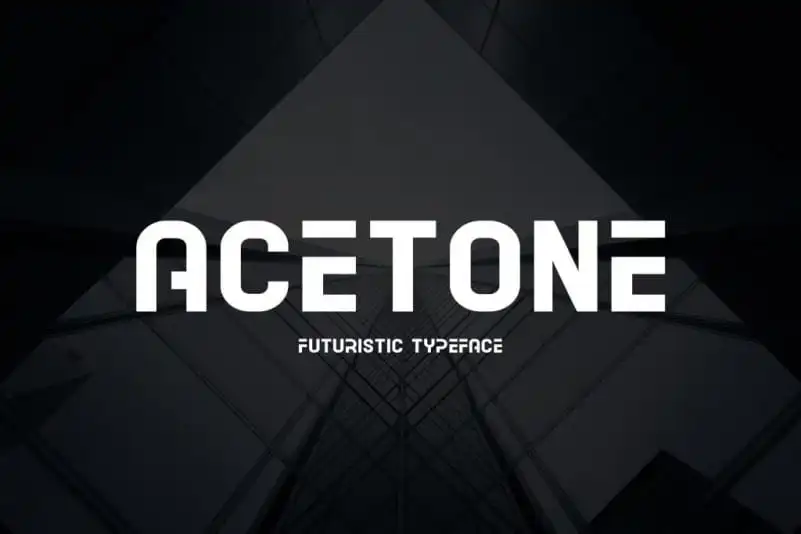
A Acetone Display Font é uma novíssima fonte tipo sans serif que surge com uma aparência futurista e moderna. Desenvolvida pelo typefactory, esta família de fontes cria seu esqueleto moderno inspirada nas linhas dos circuitos eletrônicos. Perfeita para o design de marcas de palavras, títulos em sites ou panfletas, capas de livros e até mesmo temas interiores, a Acetone Display é uma fonte sans serif que se adapta facilmente a vários usos. É um convite à criatividade, ideal para aqueles projetos que querem transmitir modernidade e atemporalidade simultaneamente. Seja em uma marca de renome ou em um design menos formal, a Acetone Display fonte é o elemento perfeito para tornar qualquer projeto único e moderno.